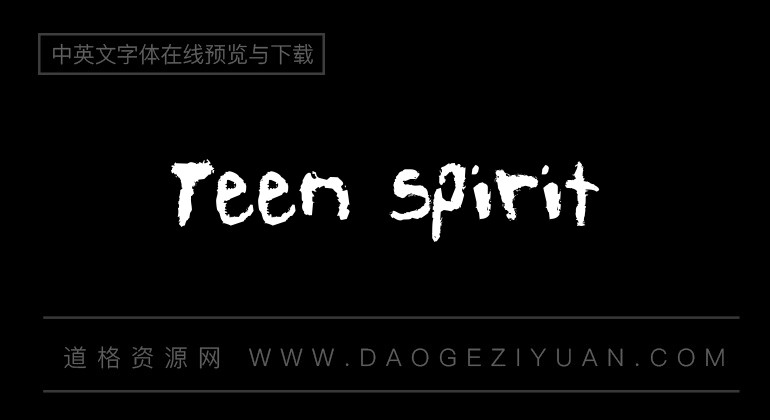
Teen Spirit 字体是一款强烈的,充满活力的手写体字体,它有着清晰的轮廓和有力的表现力,可以用来制作各种类型的印刷品,如标签,海报,海报,T恤,饰品,标志,网页等。它的特点是可以轻松地创建出精美的印刷品,使用起来也非常方便。内容介绍
Teen Spirit是一款非常不错的手写艺术字体,具有很好的视觉感,适合于文化类的宣传设计、商业类品牌的广告和产品包装设计以及个性化文字排版等较多场景。